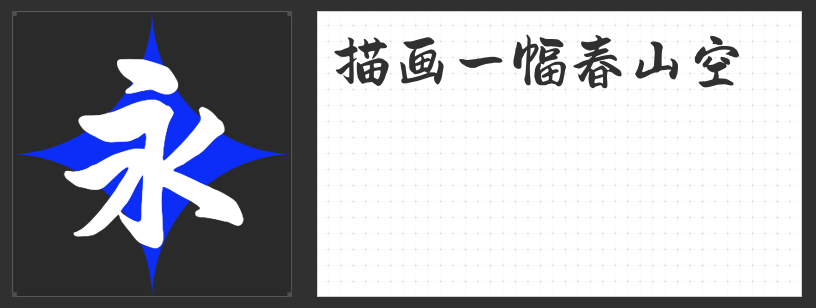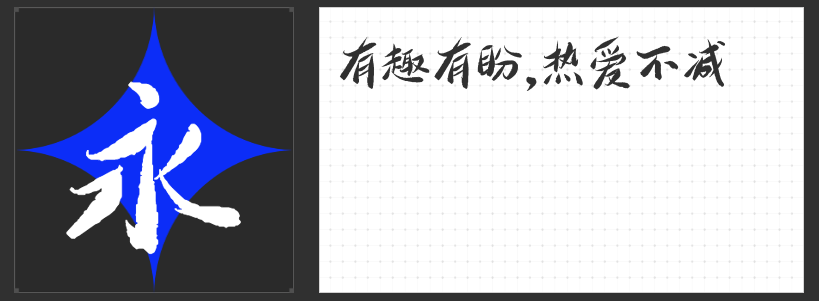
手写风潮来袭:四款风格字库字体,解锁设计新灵感
在数字化设计日益追求个性与温度的今天,手写字体以其独特的笔触韵味与人文气息,成为设计师们表达情感、传递风格的利器。以下四款精选字库字体,各具手写魅力,助你打破常规,为作品注入鲜活生命力。
一、万人字造踏歌行体
万人字造踏歌行体以方整严谨的结体为骨,匀称的笔画布局中暗藏动感韵律。其用笔方中带圆,斑驳的笔触仿佛历经岁月沉淀,笔力劲健如蓄势待发的舞者。单字间古法用笔的痕迹,既保留了传统书法的厚重感,又以现代设计语言重构了视觉张力,适合需要传递文化底蕴与力量感的设计场景。
二、高手北半川悠然体
其笔画如行云流水,随性而不失法度,毛笔的飞白与连笔间透露出洒脱的气质。这款字体弱化了结构束缚,以自由为魂,适合追求自然表达的设计项目,让文字成为情绪的延伸。
三、造字侠陈坤风行简繁
风行体以行书为基,笔画窈窕秀丽,结构洒脱中见章法。圆融的用笔与恰到好处的点睛之笔,使字形饱满而不臃肿,仿佛每一笔都蕴含着呼吸的节奏。其简繁双版本设计,兼顾实用性与艺术性,适合需要兼顾传统与现代审美的设计需求。
四、造字侠醉春风简繁 苍劲
造字侠醉春风简繁 苍劲以自由率真为魂,单字结构周正中透着松弛感,点画圆润如春风拂面。笔画粗细过渡自然,灵动的走势赋予字形独特的生命力,仿佛每个字都在纸上跳跃。这款字体既有孩童涂鸦的天真,又不失书法的功底,适合需要传递活力与亲和力的设计场景。
四款字体,四种手写哲学,或古朴、或随性、或雅致、或灵动,为设计提供多元表达可能。让文字不再只是信息的载体,更成为情感的共鸣者与风格的塑造者。